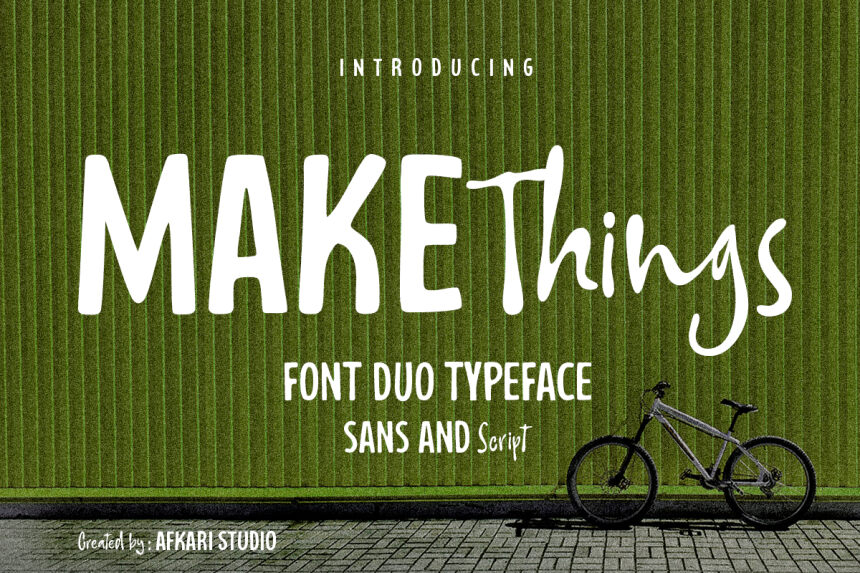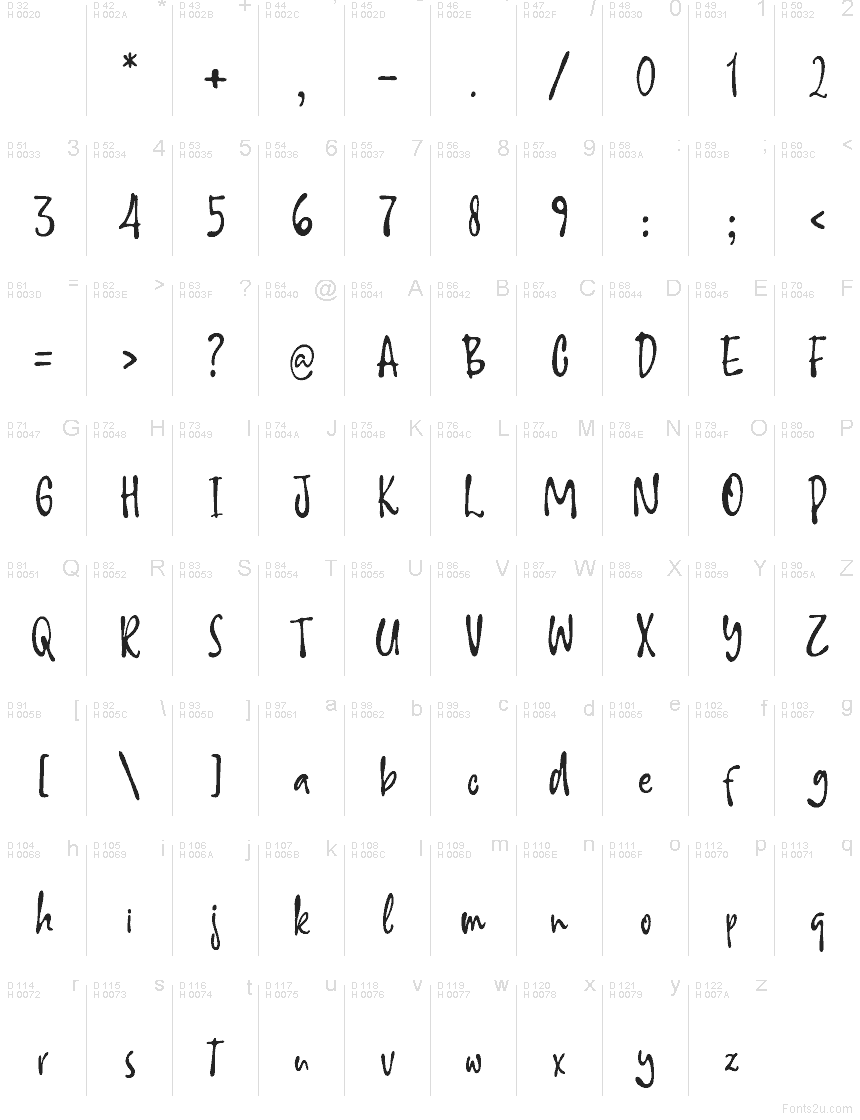
Make Things Script do Afkari Studio é uma fonte manuscrita tipo brush gratuita, com uma energia descontraída e vibrante. As letras misturam traços verticais que lembram pinceladas com junções arredondadas, fazendo com que a fonte pareça ter sido feita de forma espontânea e confiante, sem aquele acabamento excessivamente polido.
Adapta-se perfeitamente a branding casual, menus de cafés, embalagens, cartões de felicitações e gráficos curtos para redes sociais onde você deseja uma escrita com toque humano e levemente improvisado. Como é uma fonte gratuita, é especialmente útil para títulos, capas e logotipos curtos, já que os traços verticais longos e o dinamismo do design conferem às palavras uma presença manuscrita marcante.